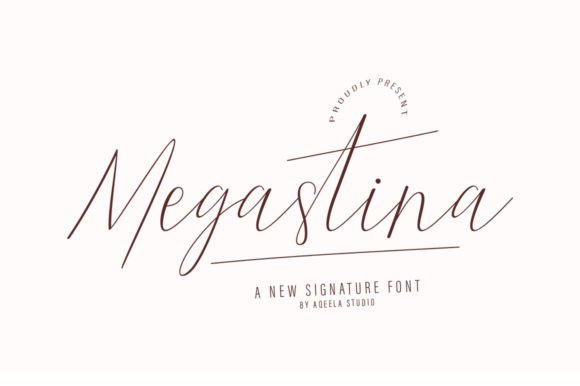
Megastina
適切なデザイン要素を見つけるのは難しい場合がありますが、Megastinaは作品を即座に引き立てる優れたコレクションを提供します。
精密に作られたMegastinaは、クリーンなベクター、滑らかなタイポグラフィ、そして安心のための商用ライセンスを提供します。
POD(オンデマンド印刷)製品、結婚式の招待状、またはソーシャルメディアのグラフィックを作成している場合でも、Megastinaは理想的です。